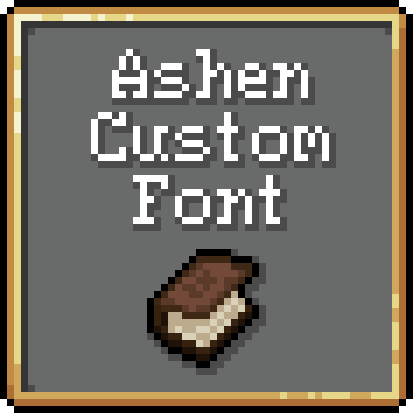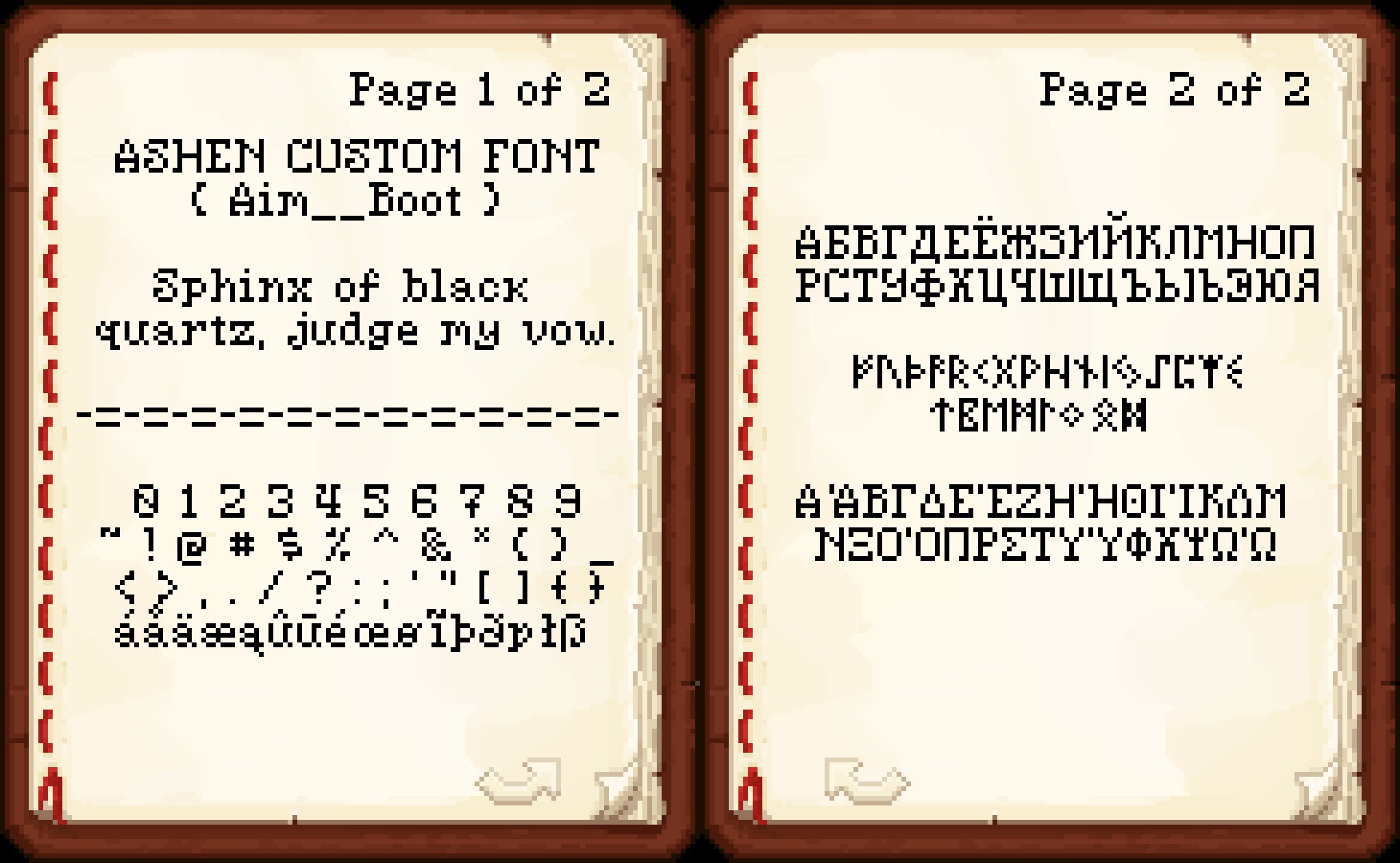
Ashen 16x Custom Font
Индивидуальный шрифт для уникального оформления вашего мира.
Описание мода
Погрузитесь в уникальный мир с модом Ashen 16x Custom Font! Этот мод полностью преобразует стандартный шрифт Minecraft, заменяя его на художественный шрифт с засечками, который был создан с нуля. Идеально подходит как для знатоков Ashen 16x, так и для тех, кто хочет использовать оригинальный шрифт с другими текстурными пакетами. С полным набором символов, этот шрифт поддерживает не только латиницу, но также такое множество алфавитов, как алфавит Иллажеров и Стандартный Галактический шрифт (шрифт enchanter).
Уникальные особенности мода
• Полная поддержка алфавитов: настраивайте текст в Minecraft так, как вам нравится, без ограничений.
• Отлично сочетается с Ashen 16x: мод был специально разработан для использования вместе с этим текстурным паком.
Обратите внимание, что при использовании шрифта Ashen 16x Unicode-символы, такие как деванагари, не будут перезаписаны, сохраняя оригинальный функционал игры. Этот мод идеально подойдет для игроков, которые хотят привнести индивидуальность и атмосферу в свои приключения в Minecraft. Попробуйте Ashen 16x Custom Font и дайте вашему миру новый голос!